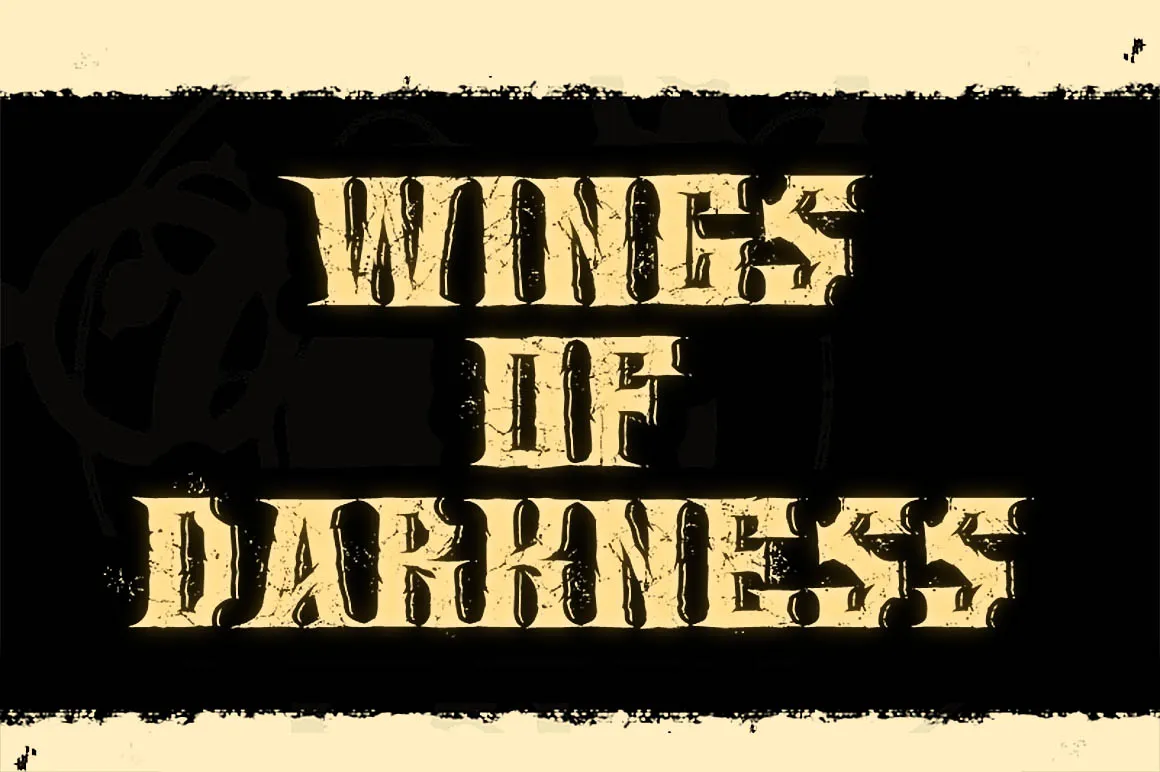
A WINGS OF DARKNESS Font é uma elegante tipografia serif que brota da mão do designer Hamilton. Esta elegante fonte traz um toque vintage e grunge, perfeita para seus novos projetos criativos. Se você está procurando por um estilo que combine a modernidade com uma atmosfera nostálgica, WINGS OF DARKNESS pode ser a solução ideal. Suas linhas sóbrias e detalhes sofisticados vão dar um toque inovador ao seu design gráfico. Essa fonte é perfeita para criar mensagens impactantes ou adicionar um brilho diferente aos seus materiais de marketing, sem deixar de manter a elegância que tanto valorizamos na serif. Seja você um designer gráfico profissional ou iniciante, WINGS OF DARKNESS Font certamente não lhe decepcionará.